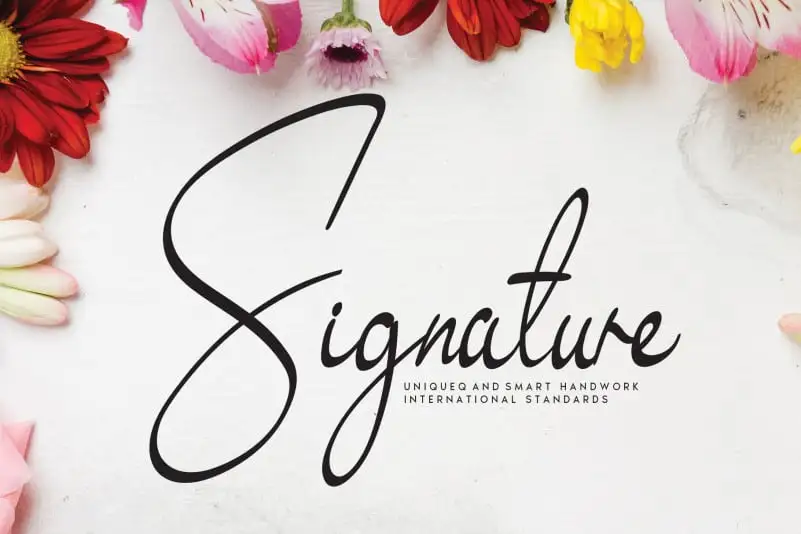
Signature – Exquisite Handwritten Font – Download Grátis
Signature – Exquisite Handwritten Font é uma elegante tipografia que transmite a sofisticação dos traços da caligrafia ao mesmo tempo que oferece um toque contemporâneo e atual. Inspirada na perfeição do calligráfico, ela mantém seus influências legítimas enquanto apresenta uma aparência fresca e vibrante. Este é o tipo de fonte perfeito para qualquer projeto exigente, desde cartões personalizados até editoriais digitais modernas. Tornando-se sua escolha ideal, Signature – Exquisite Handwritten Font trará seu trabalho à um nível superior.